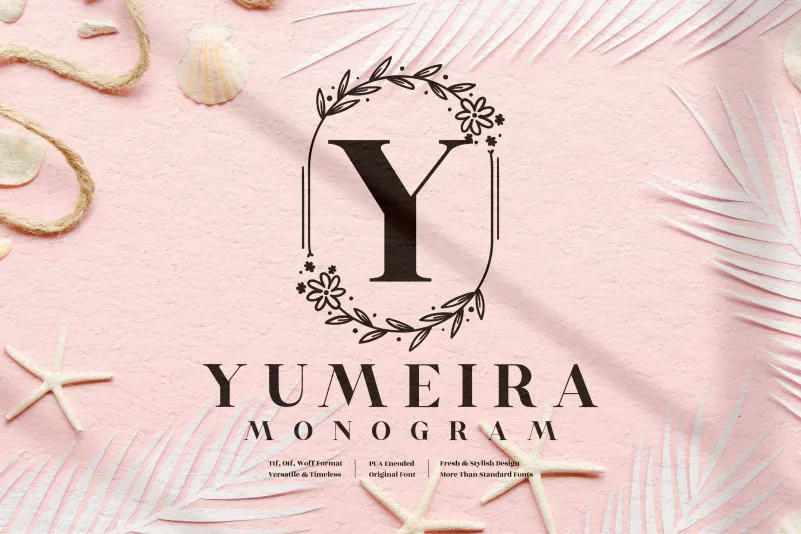
Yumeira Monogram Font – Download Grátis
A Yumeira Monogram Font é uma elegante tipografia ornamental que transmite sofisticação através de suas ornamentações de folha luxuosa. Perfeita para quem busca um toque refinado em design gráfico, sua aparência arredondada e rica em detalhes a torna ideal para criações de anúncios de casamento incrivelmente bonitos, arte de cartões de visita suave e elegante, posts de mídia social atrativos e logos memoráveis. Ela também é perfeita para criar cards de felicitação adoráveis. Esta fonte foi criada pelo designer perspectype e é uma ótima escolha para aqueles que buscam personalidade e sofisticação em sua tipografia, tornando-a versátil o suficiente para adaptar a qualquer projeto visual.